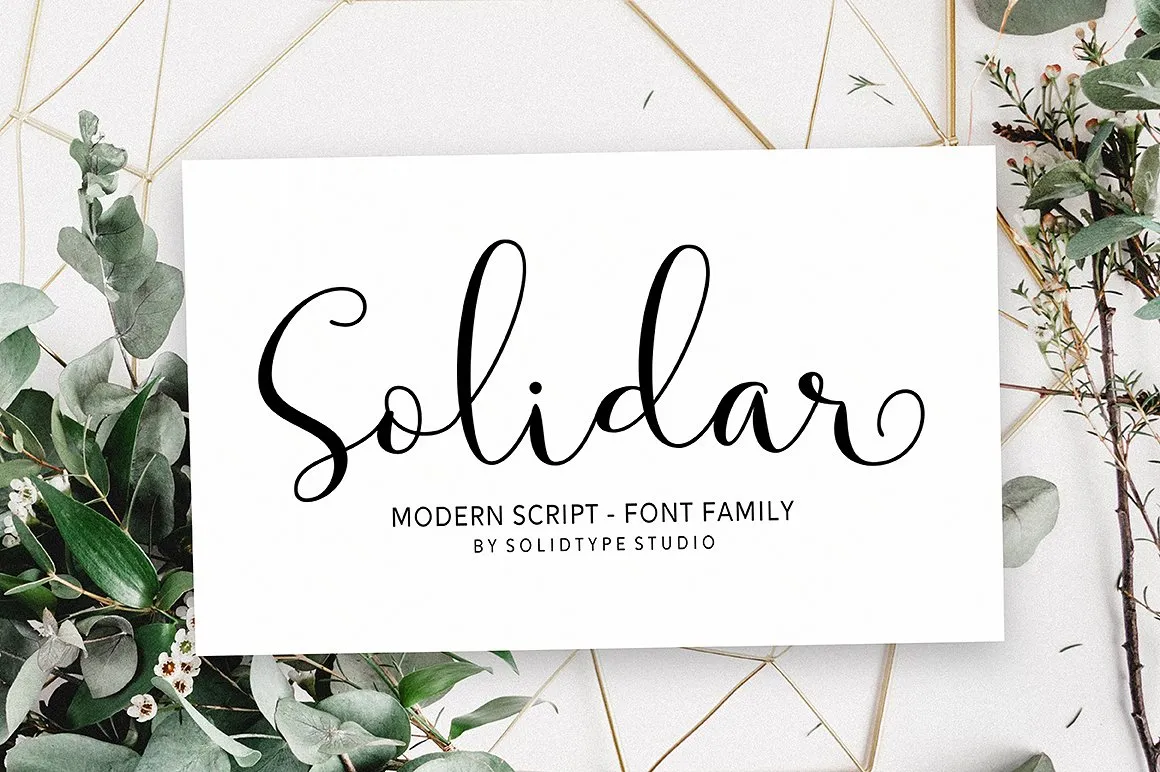
Solidar Script Font
A Solidar Script Font é uma família moderna de script criada por Hamilton. Introduzida no mercado, esta fonte oferece um toque elegante e uma aparência leve e agradável. É perfeita para criar logotipos, cartas pessoais, marcações, frases inspiradoras, impressões digitais, convites de aniversário e até mesmo decoração personalizada. Um destaque importante é sua abordagem versátil, com alternativas presentes em todas as minúsculas, alongando e desenhando a escrita tanto no início quanto na final. Essas características adicionam um toque único e encantador à fonte, tornando-a uma escolha inteligente para qualquer projeto que busque um ar elegante e atemporal. Esta font é o seu parceiro ideal para criações gráficas criativas e sofisticadas, oferecendo inúmeros recursos que podem ser usados para personalizar ainda mais suas produções digitais ou impressas.